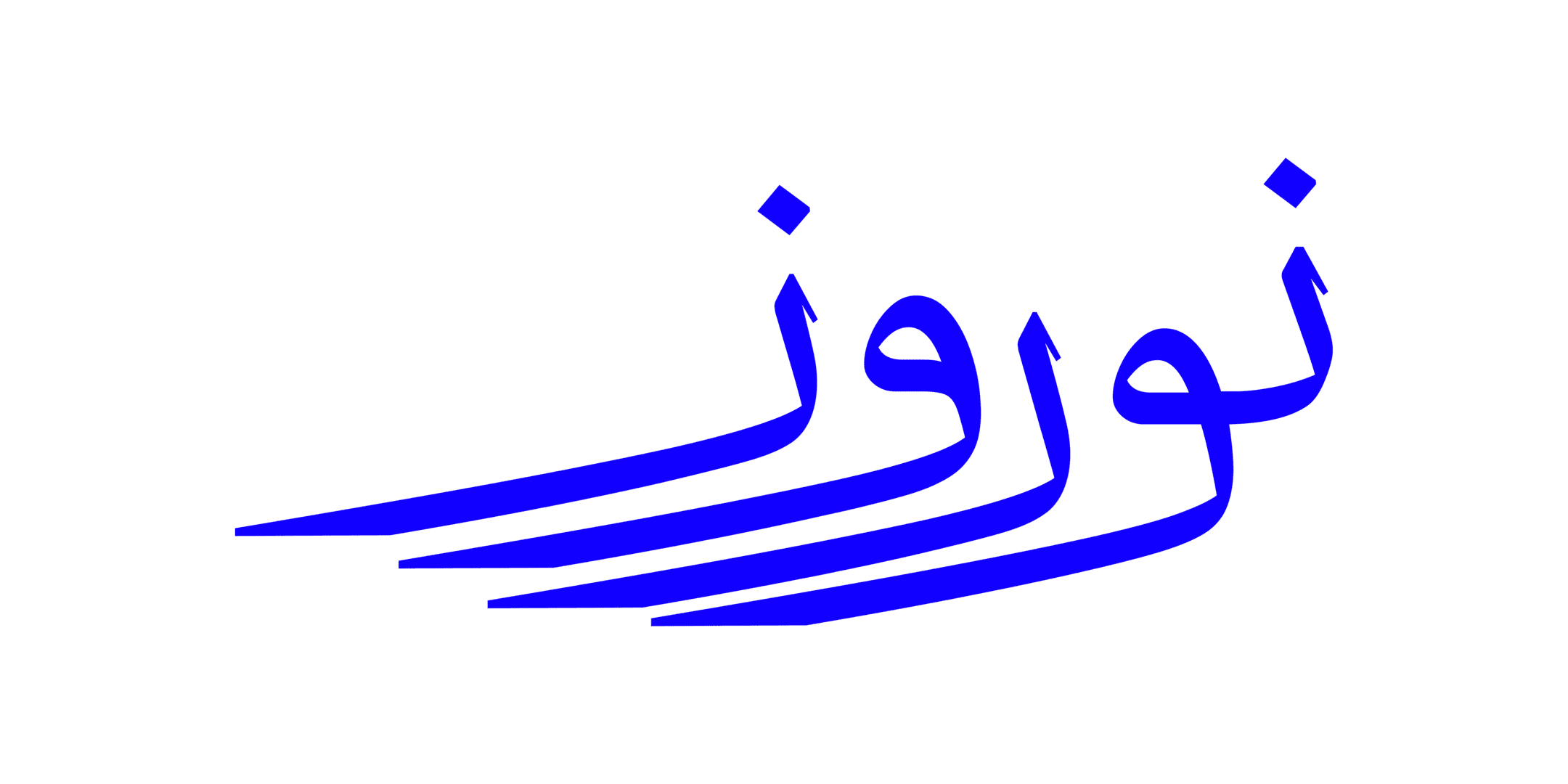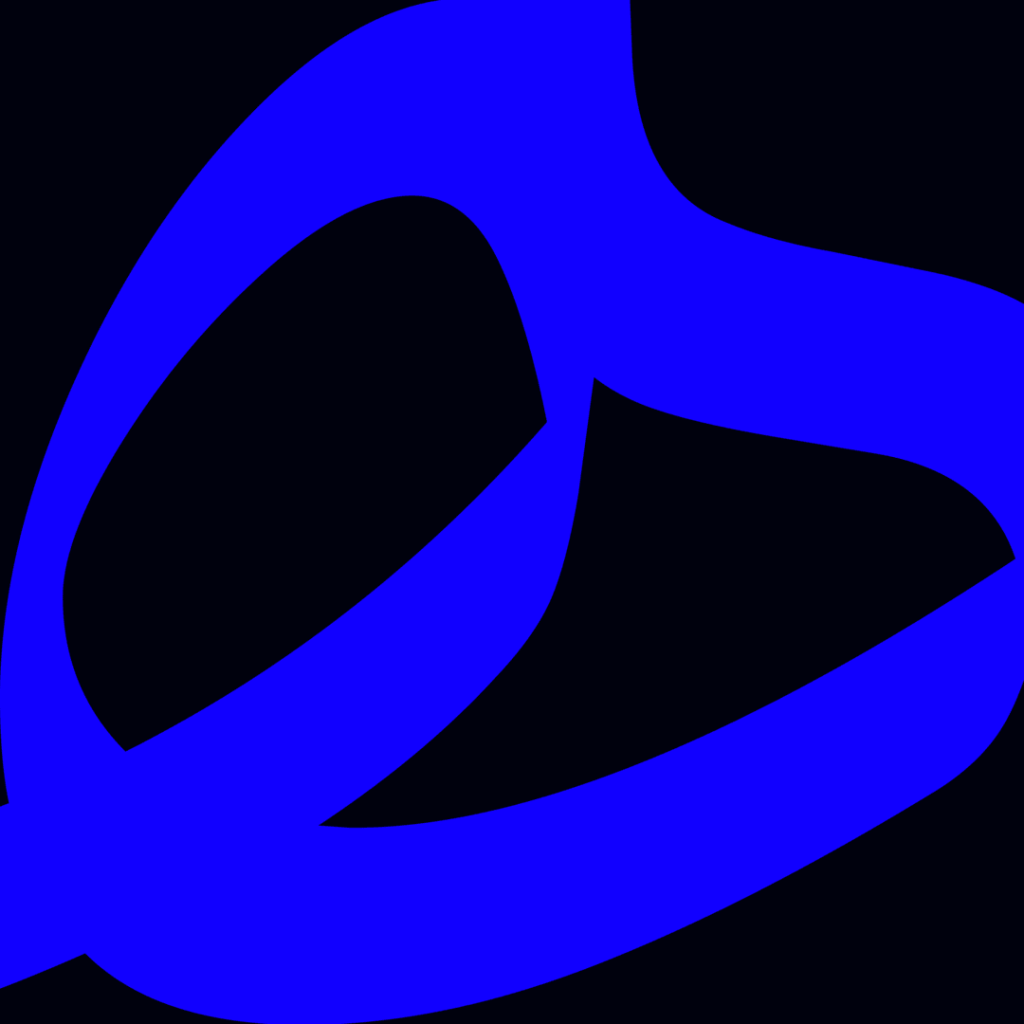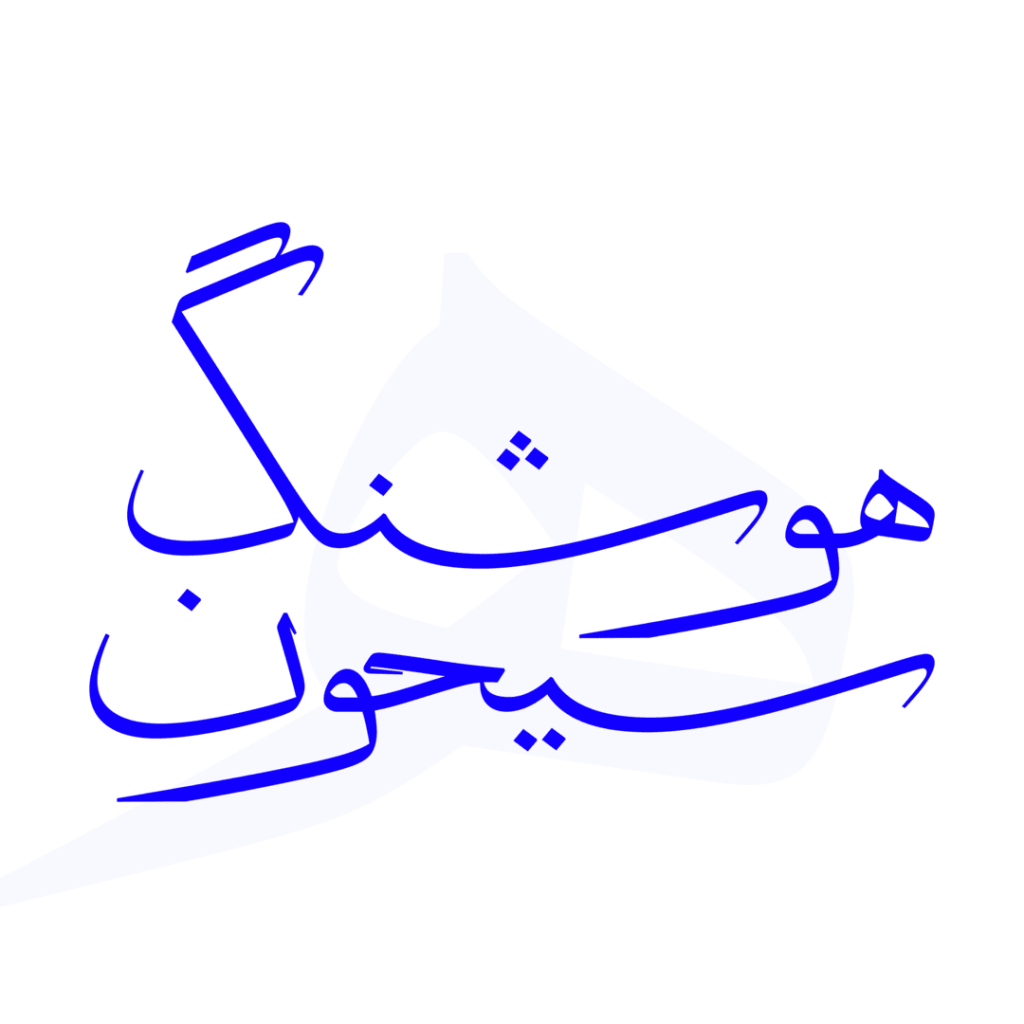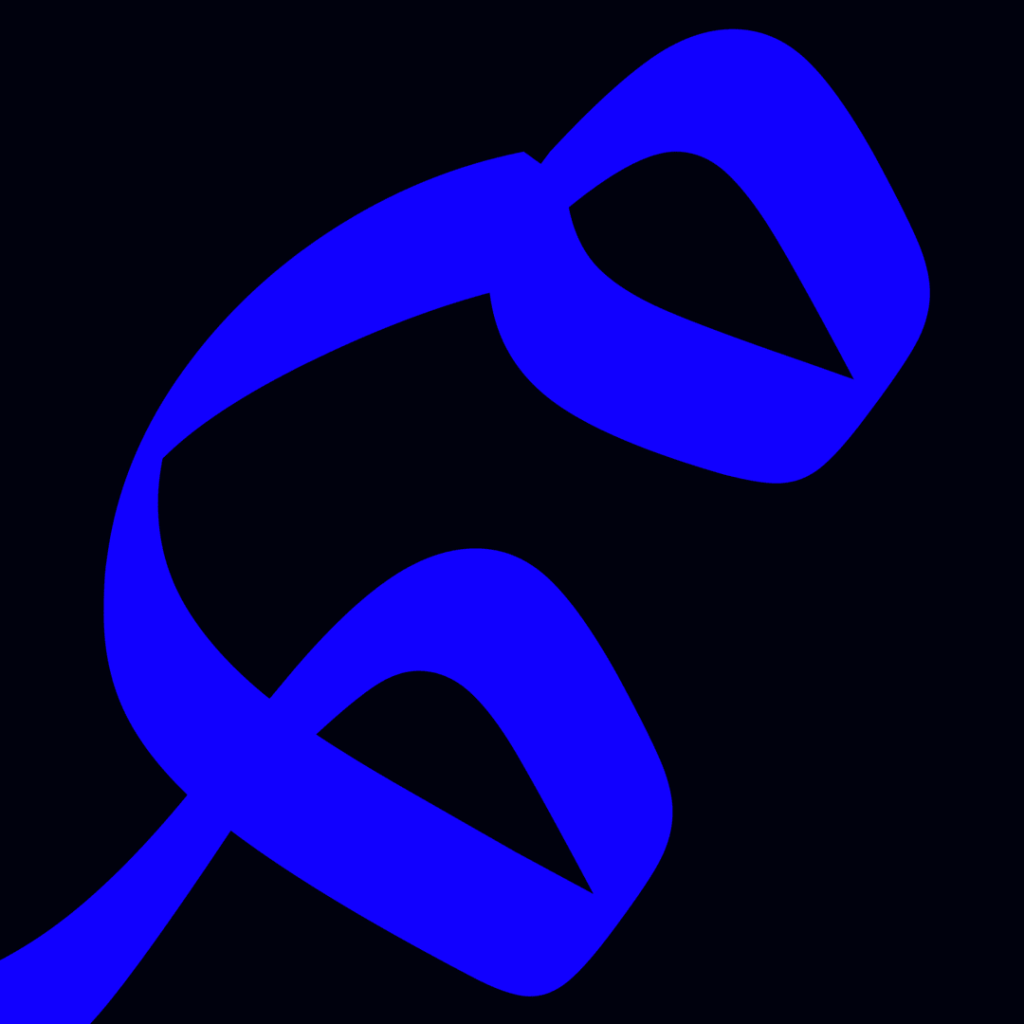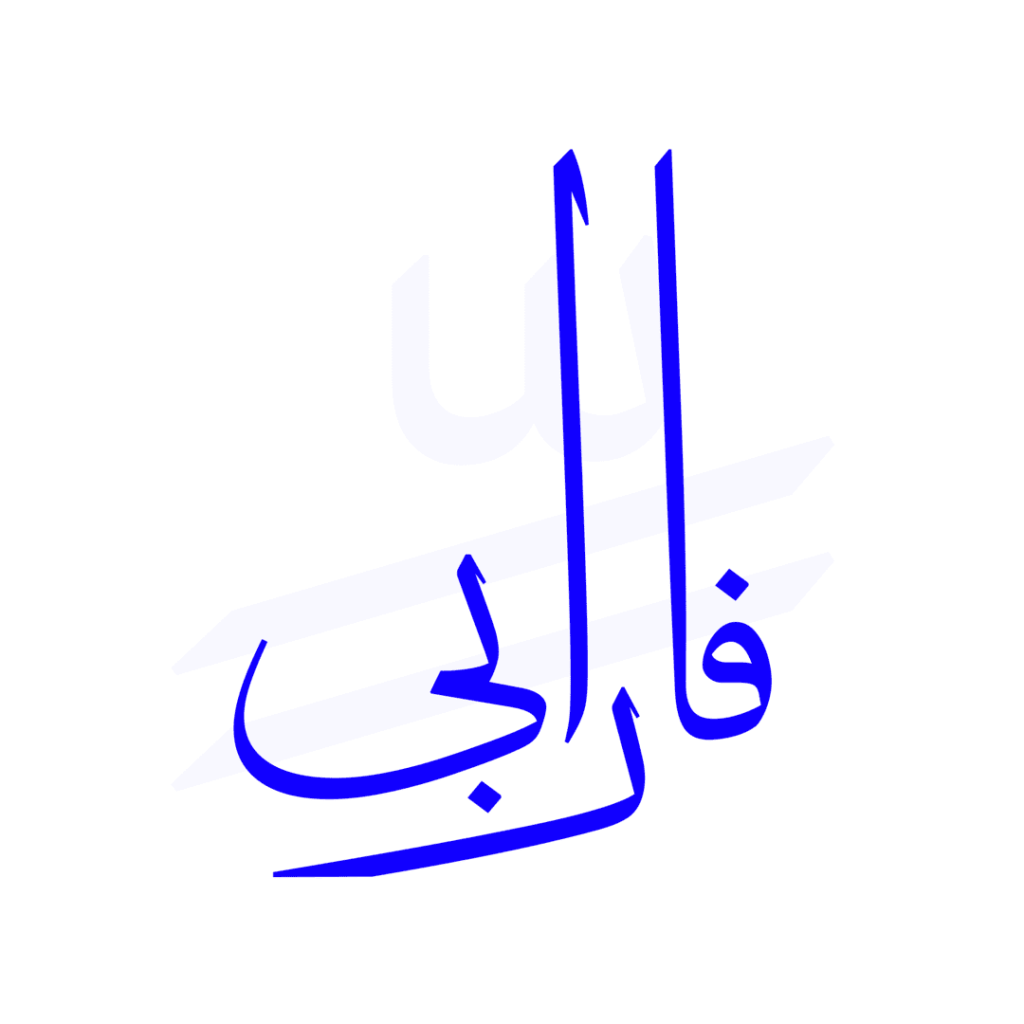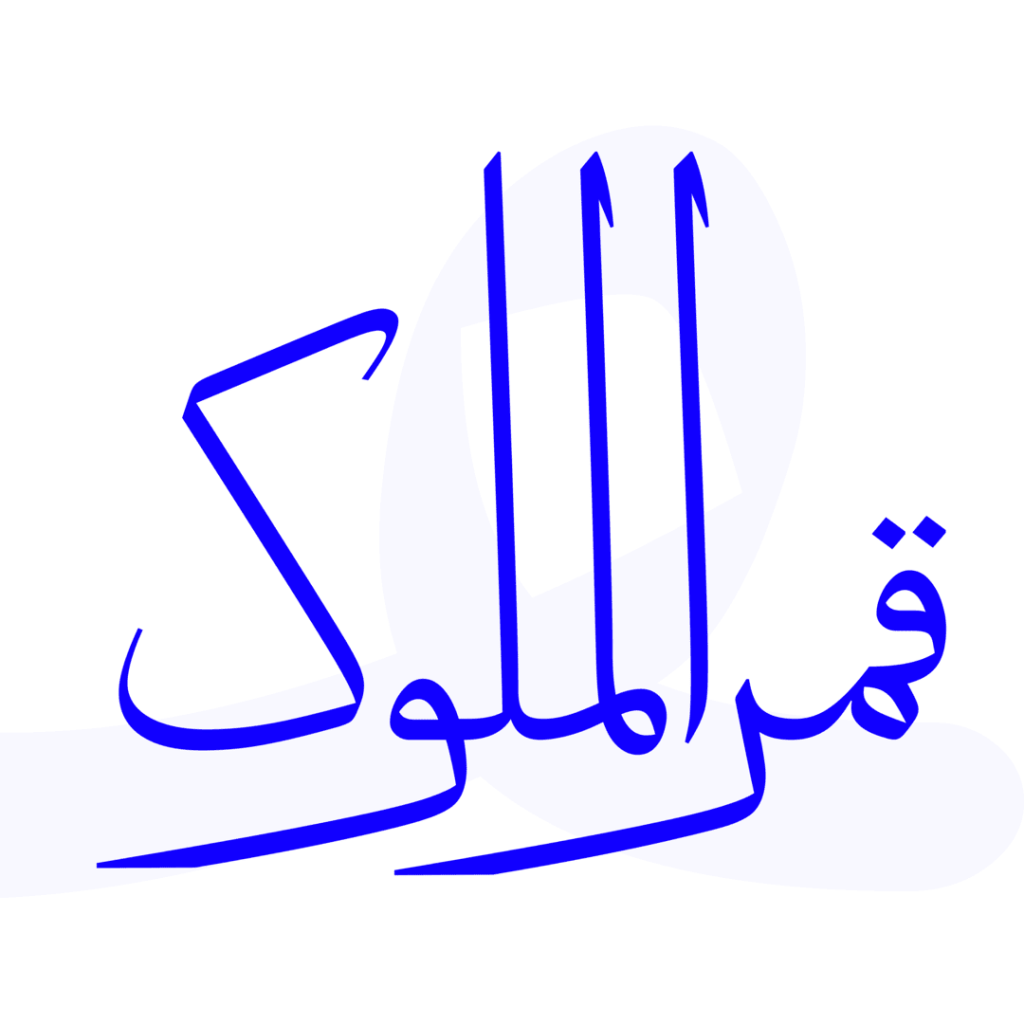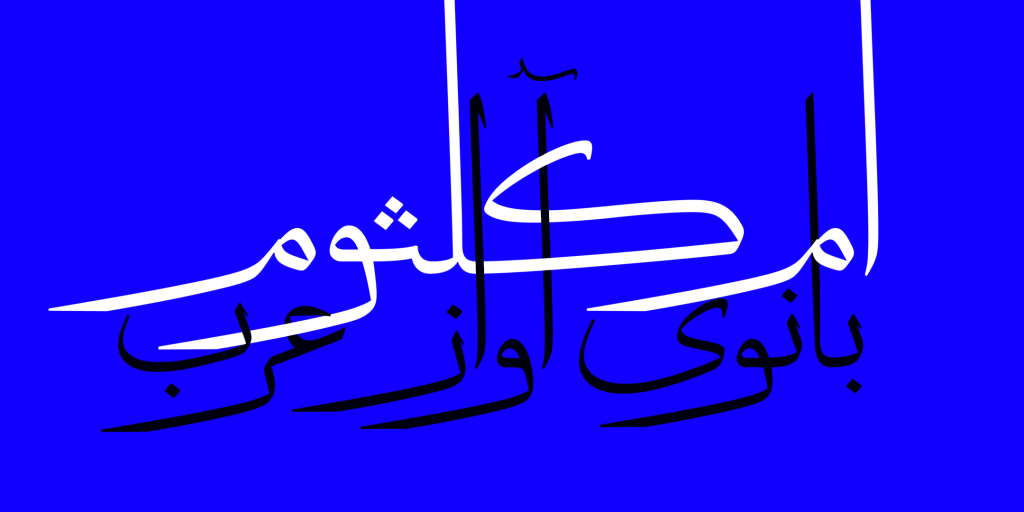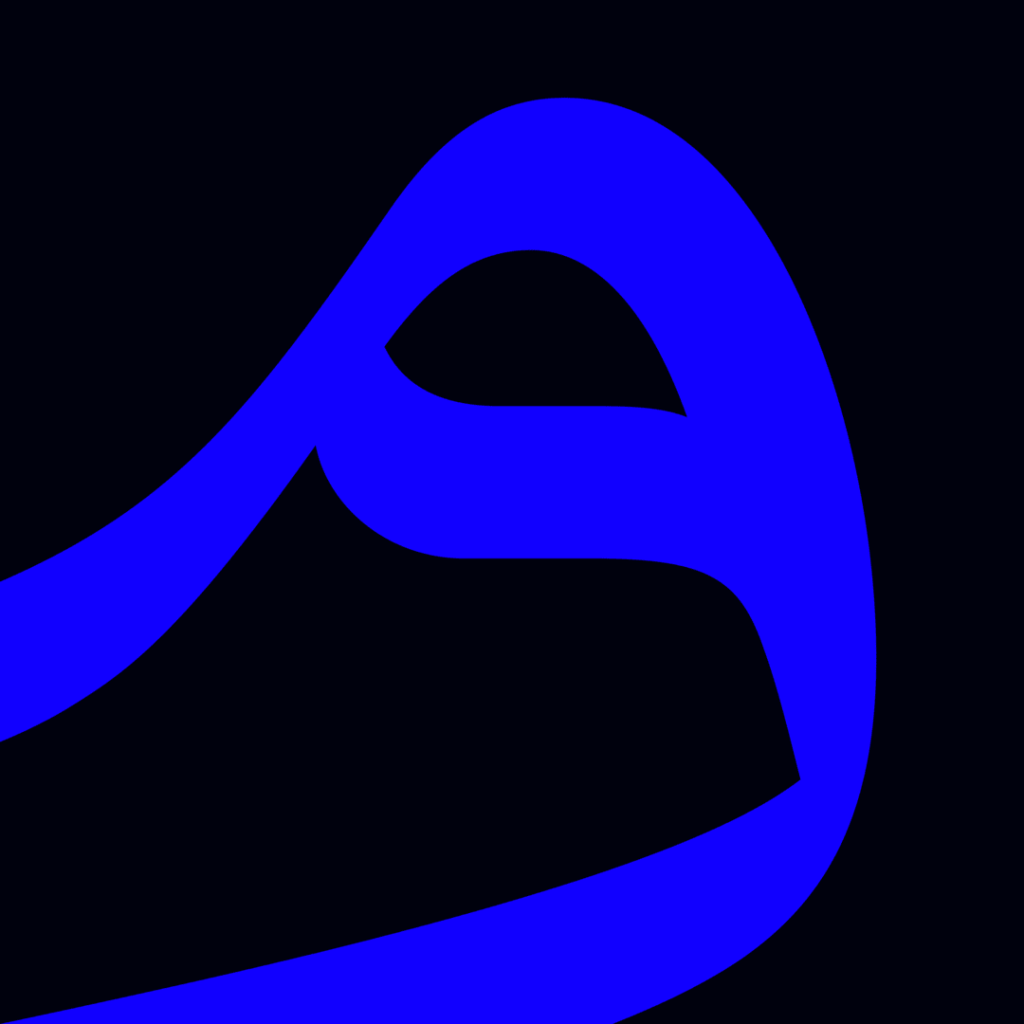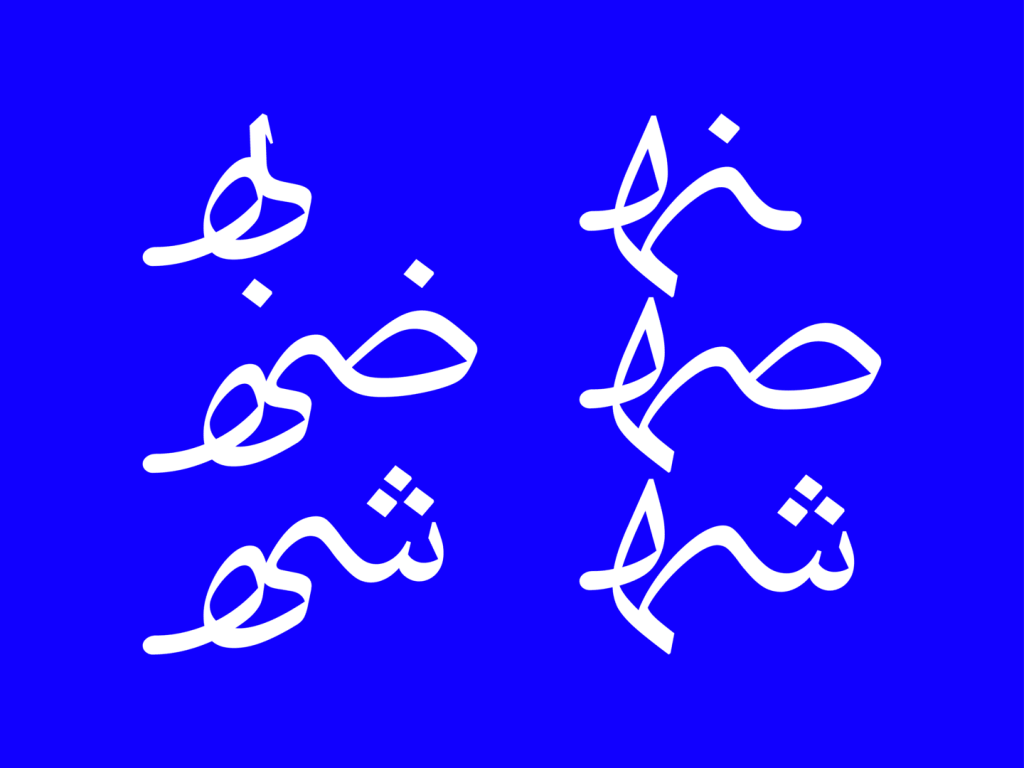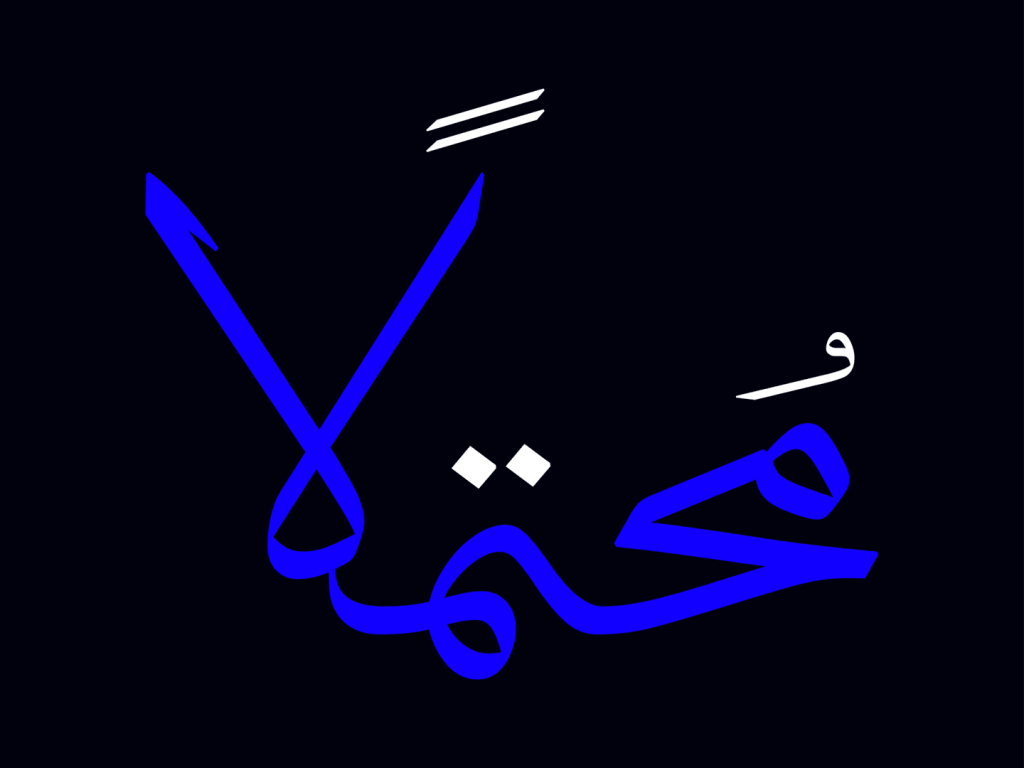
فونت دانگ (dang)
فونت دانگ بر اساس خط محقق طراحی و ایجاد شده است. محقق خطی با شکوه از اقلام سته به شمار می رود که با قد و قامتی کشیده و فواصلی منظم زیبایی های خاص خود را دارا می باشد. می توان اینگونه توضیح داد که یک دانگ و نیم خط محقق دور و چهار دانگ و نیم آن سطح است. این قلم یکی از اولین خطوطی است که به دست توانمند ابن مقله باز طراحی شد و سپس توسط ابن بوّاب رواج پیدا کرد.
دانگ مسافری حماسی از روزگاران قدیم
این قلم دارای شخصیت و روحیه ای اساطیری، حماسی و تاریخی است،گویی مسافری است کهخ از روزگاران قدیم قدم به عصر حاضر نهاده است، قد و قامت کشیدهی حروف بر روحیهی حماسی و اساطیری این تایپ فیس می افزاید. این قلم بسیار مناسب جهت مناسب استفاده در فضاهای مختلف گرافیکی است.
کاربرد دانگ در عناوین تیتر ها و متون در مطبوعات، تبلیغات، فضاهای وب و دیجیتال و … که دارای فضای رسمی با تم و محتوای تاریخی و اساطیری و هنری و … می باشد.
دانگ و دارا بودن ترکیبات و حروف جایگزین
این قلم همچنین از قابلیت پر سود و فایده حروف جایگزین که هم سبب افزایش پویایی و تنوع و هم بر زیبایی تایپ فیس می افزاید بهره مند است. دارای لیگچرها و حروف جایگزین زیادی میباشد که دست طراحان و تایپوگرافرهارا باز می گذارد. در تصاویر نمونه از این قلم می توانید این تونع و جایگزینی را مشاهده کنید.
پشتیبانی فونت دانگ از چندین زبان مختلف
این تایپفیس دارای پشتیبانی از طیف گسترده ای از زبان های مختلف از جمله زبان های عربی/اردو/کوردی و انگلیسی می باشد. و دست پری در این زمینه دارد. سعی بر تفاهم و هم نشینی در حروف های و لیگچر ها از لحاظ طراحی و فرم ساختاری در هر کدام از زبان های یاد شده انجام گردیده است. همچنین در زبان لاتین داری حروف و گلیف هایی است که میتواند برای متن و عنوان کاربرد داشته باشد.
از دیگر خصوصیات این قلم می توان به برتری سطح به دور و داشتن طره در برخی از حروف نظیر ” الف/ ب/ ج/ د/ و/ ط ” اشاره نمود . انتهای حروف ” و/ ر/ م ” به صورت آزادانه نوشته و ارسال میشدند. کلمات حول محور خط کرسی تجمع پیدا میکنند زیرا کشیدگی عمودی برخی حروف را می توان مشاهده کرد و این امر موجب ایجاد سبکی و سنگینی در متن میشوند . همچنین به دلیل طول کشیده ارسالهای “و” “ر” “م” گاهاً این حروف باهم ریتم ایجاد میکنند یا برای حروف برای کلمات بعدی فضا خالی میکنند تا حروف بعدی را در دل خود جای دهند.